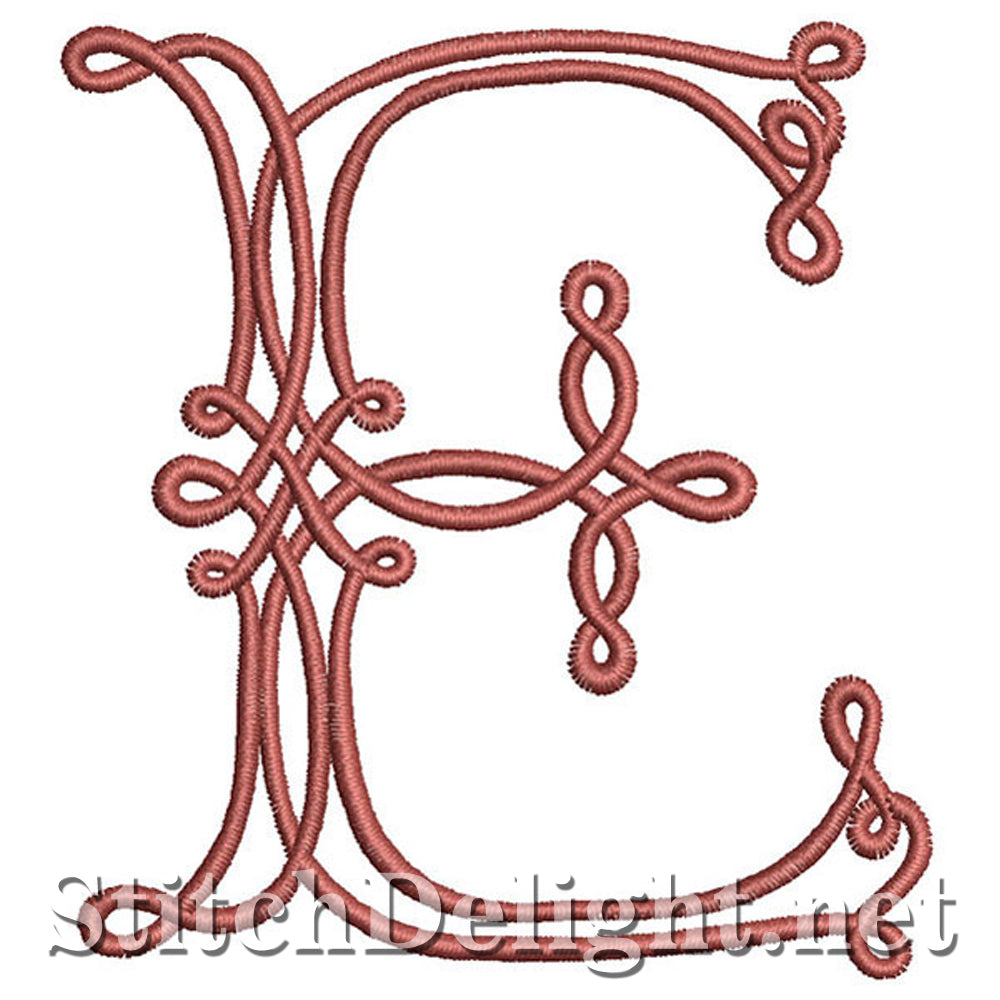
SDS1199 Keltisch lettertype E
Gedetailleerd Keltisch lettertype, meestal voor de 4x4 borduurring, M, W en Q zijn voor de 4x7 borduurring, dus controleer de maten om er zeker van te zijn dat het in uw steekgebied past - letterhoogte is 85 mm / 3,34 inch